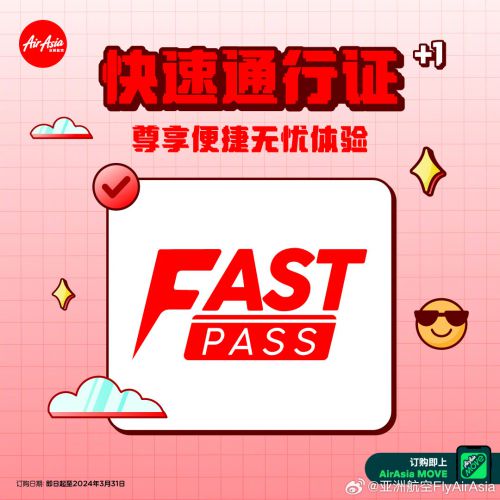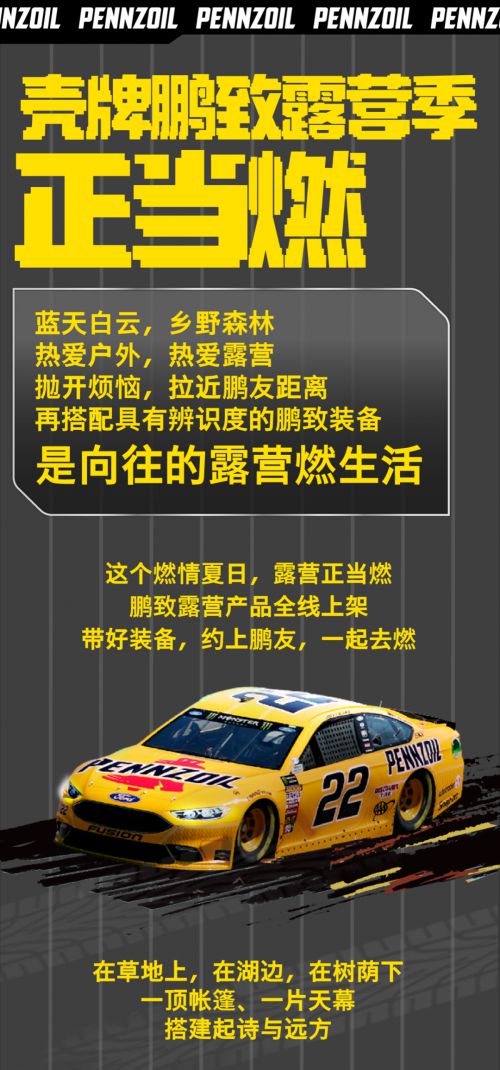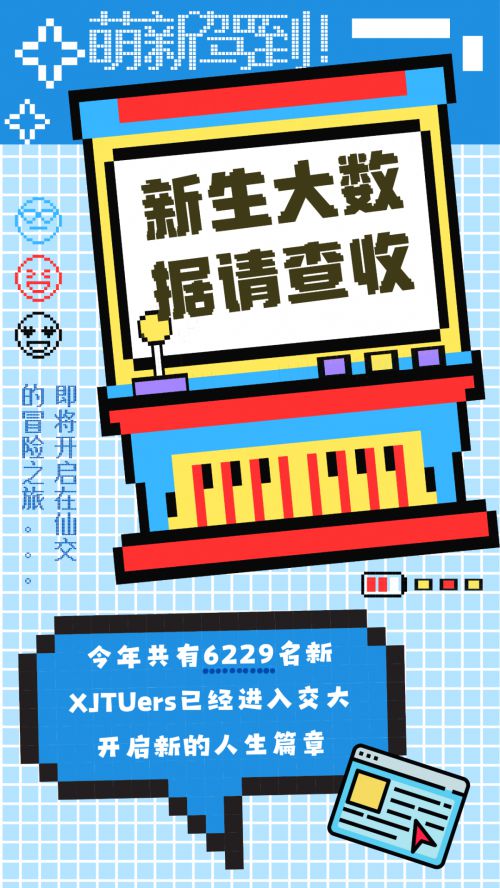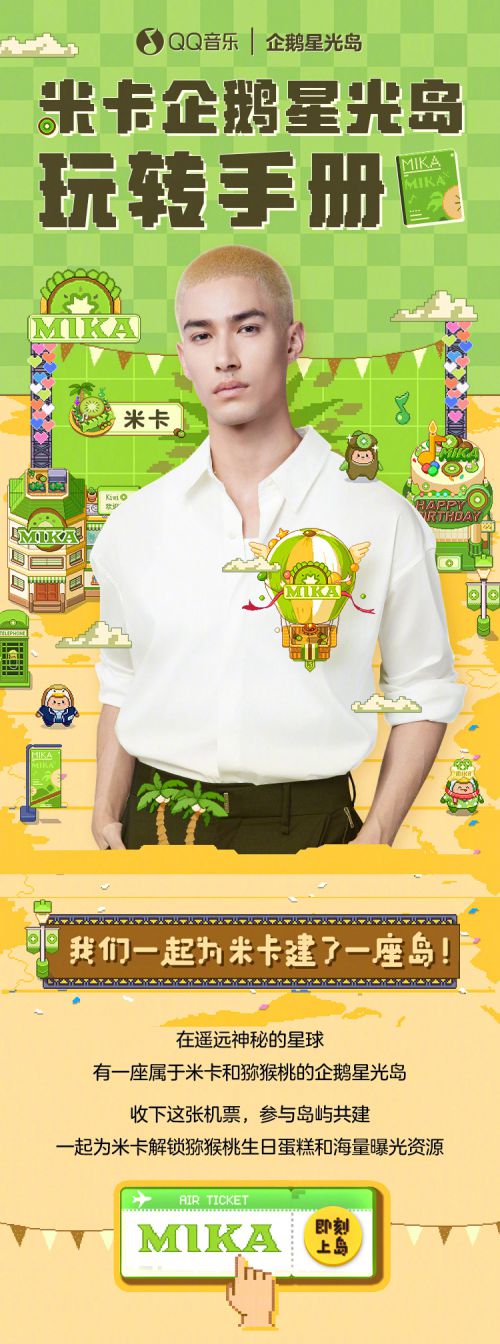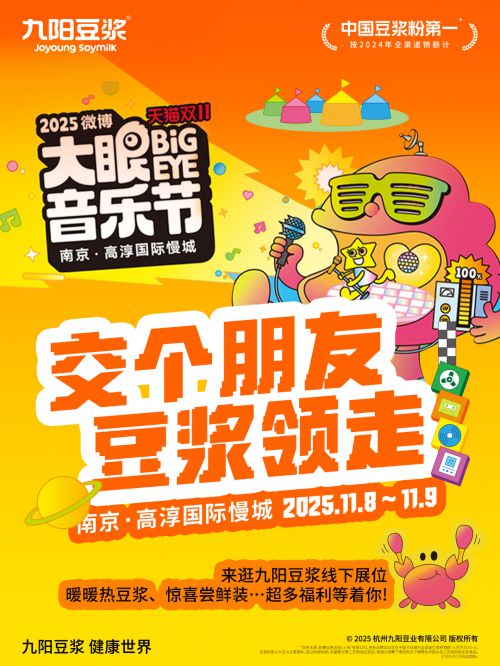
点字像素之城
点字像素之城是由点字库打造的创意字体,以复古像素风为核心,融合卡通趣味与科技质感,成为游戏界面、潮酷海报、科技产品包装的理想选择。字体结构修长,重心偏高,中宫宽博设计确保字形端正、识别度优异;笔型以像素点为基本单元拼合,方头笔画搭配均匀粗细线条,连接处以颗粒感断开,既保留8-bit复古游戏的方块美学,又通过像素颗粒传递灵动趣味。作为会员商用字体,点字像素之城兼顾设计个性与商业实用性,无论是打造怀旧主题视觉,还是凸显科技潮玩风格,都能以独特像素语言赋予作品吸睛表现力。